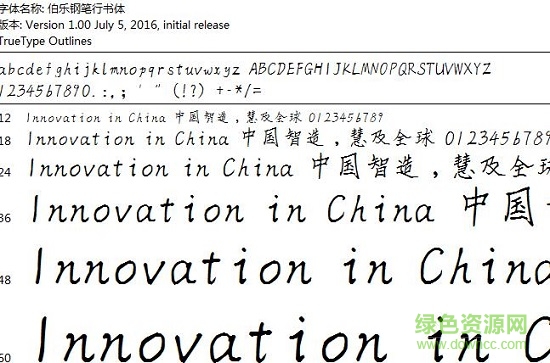
伯樂鋼筆行書體是一款專為喜歡書法自字體的朋友準(zhǔn)備的鋼筆字體,這款字體整體上看上去會(huì)覺得非常的賞心悅目,感興趣的朋友歡迎下載使用!
伯樂鋼筆行書體是一款根據(jù)鋼筆行書書法打造而來(lái)的書法字體,具有硬筆書法完美的特質(zhì),筆畫剛硬有勁,字跡如行云流水一般順暢,非常的具有欣賞價(jià)值!